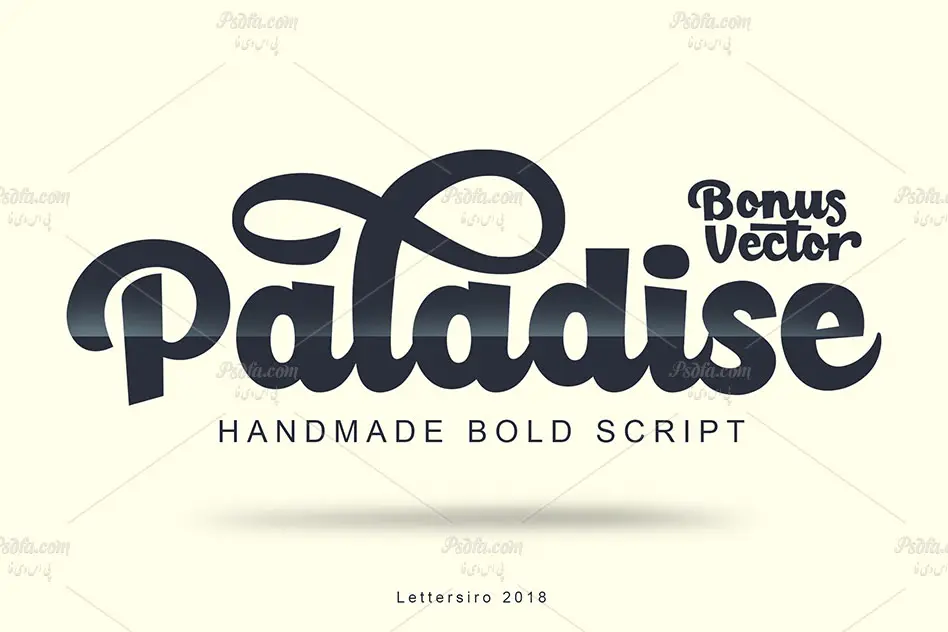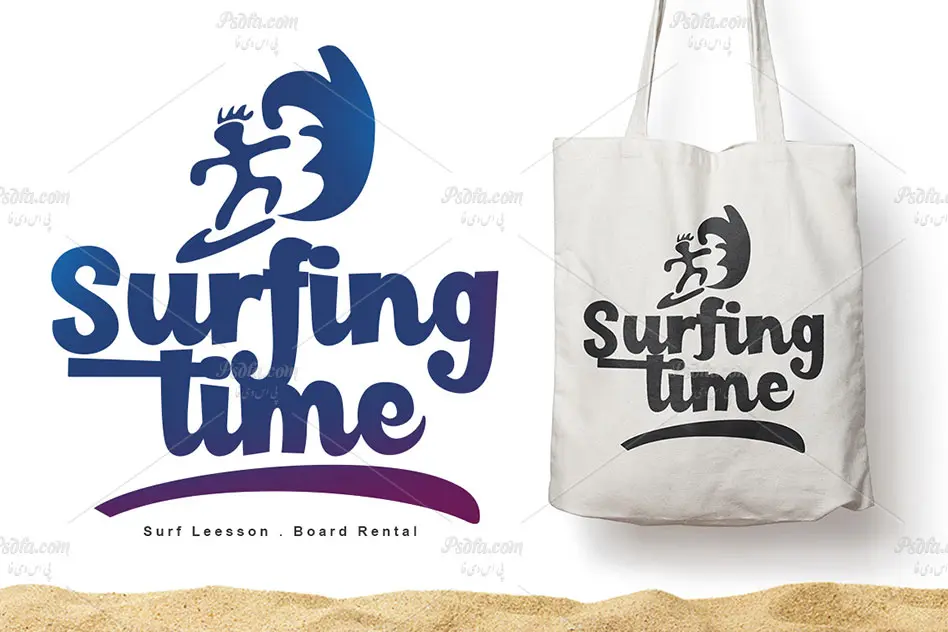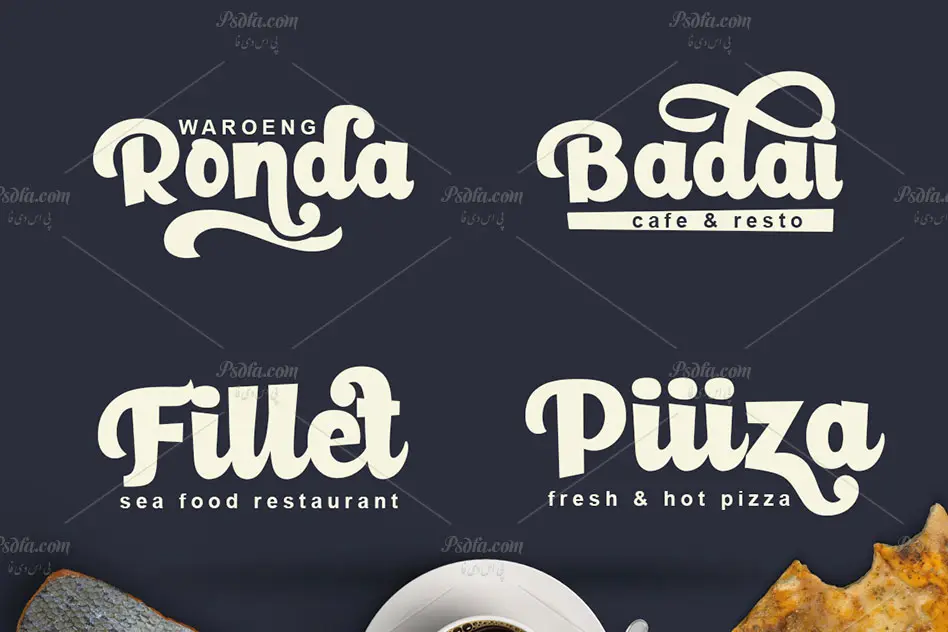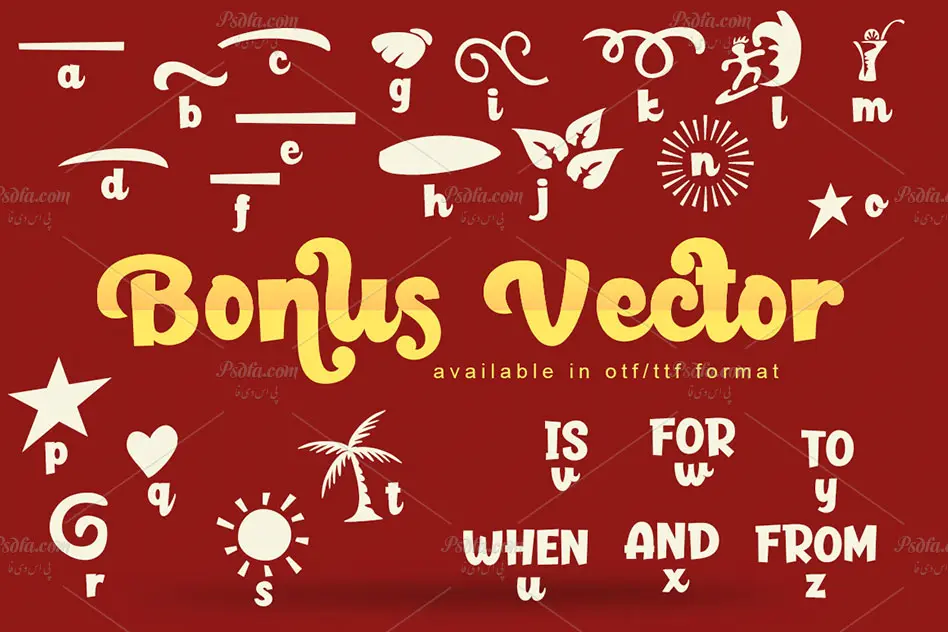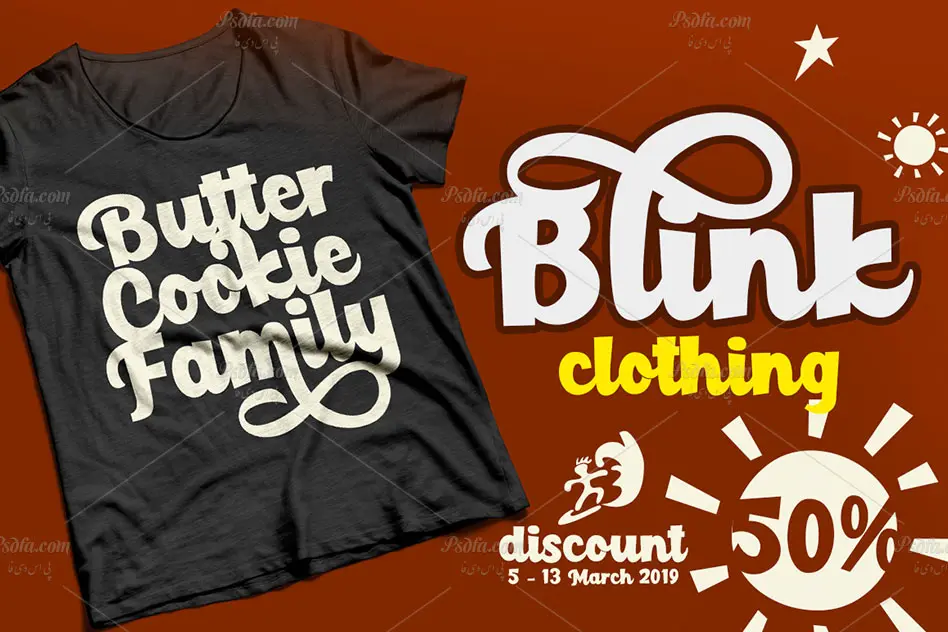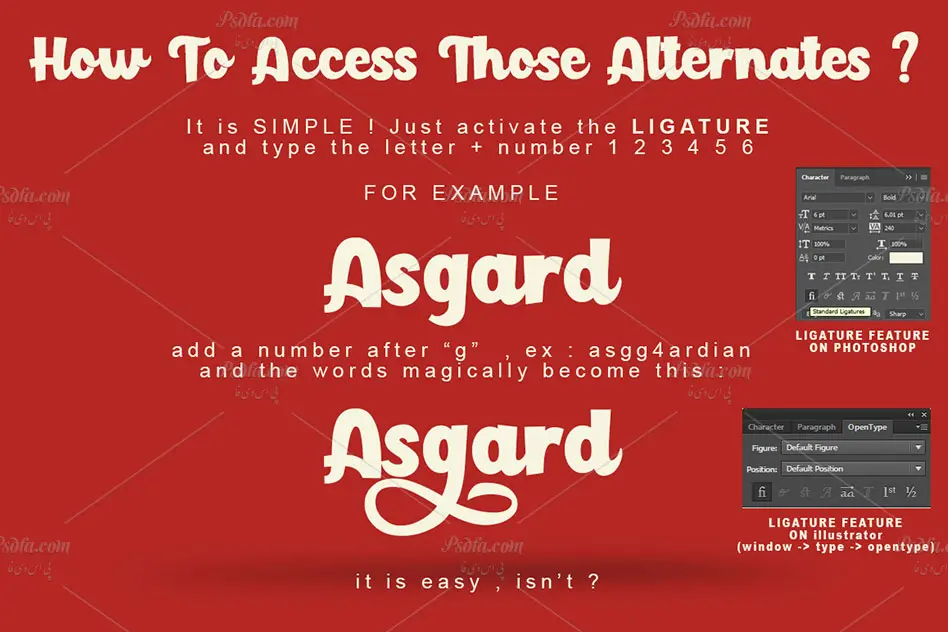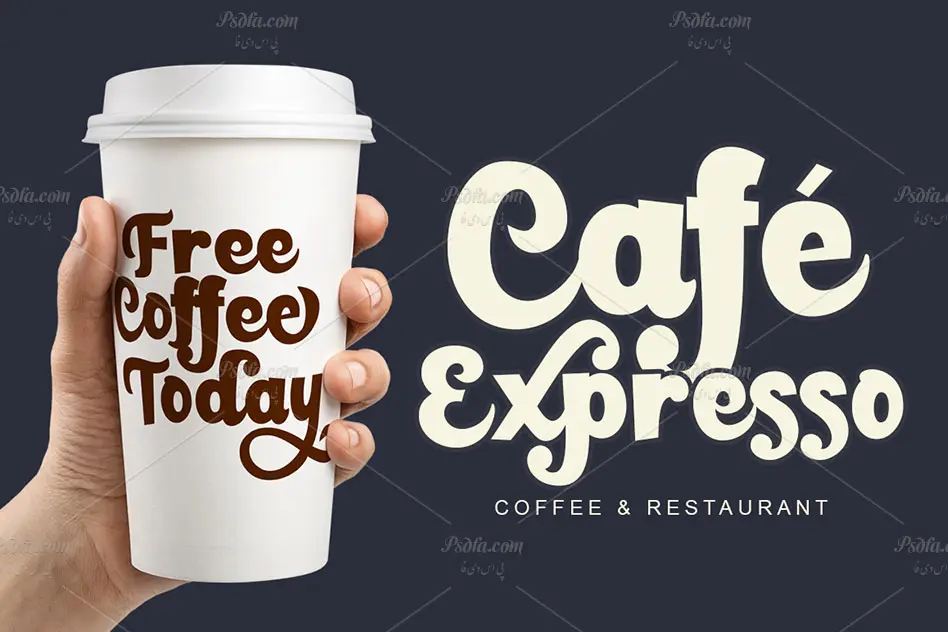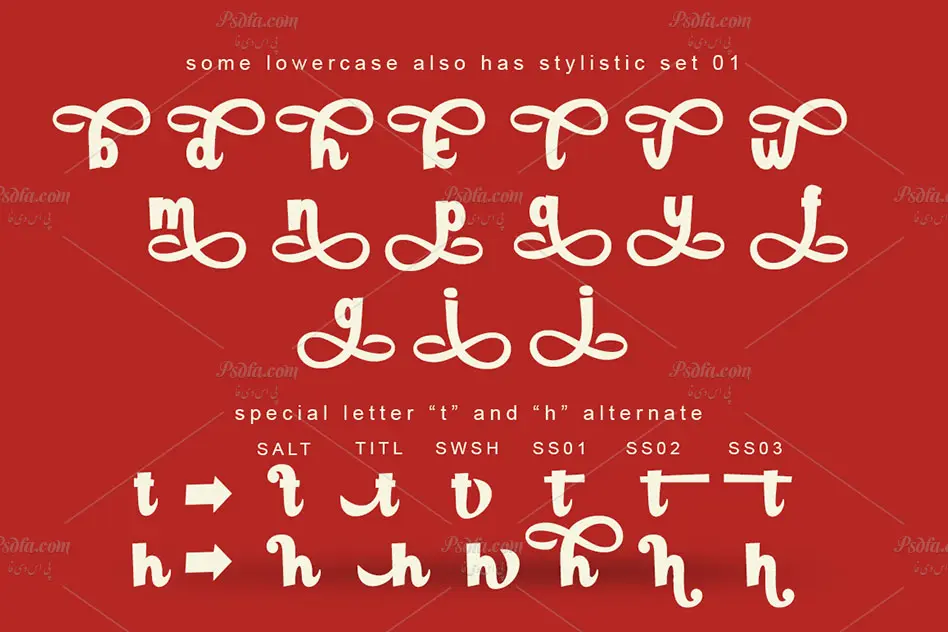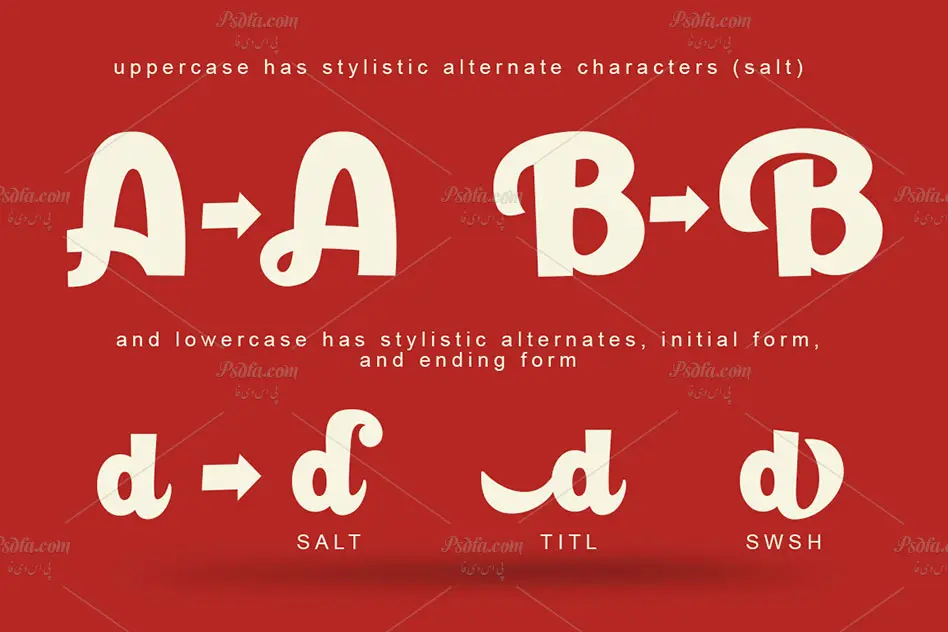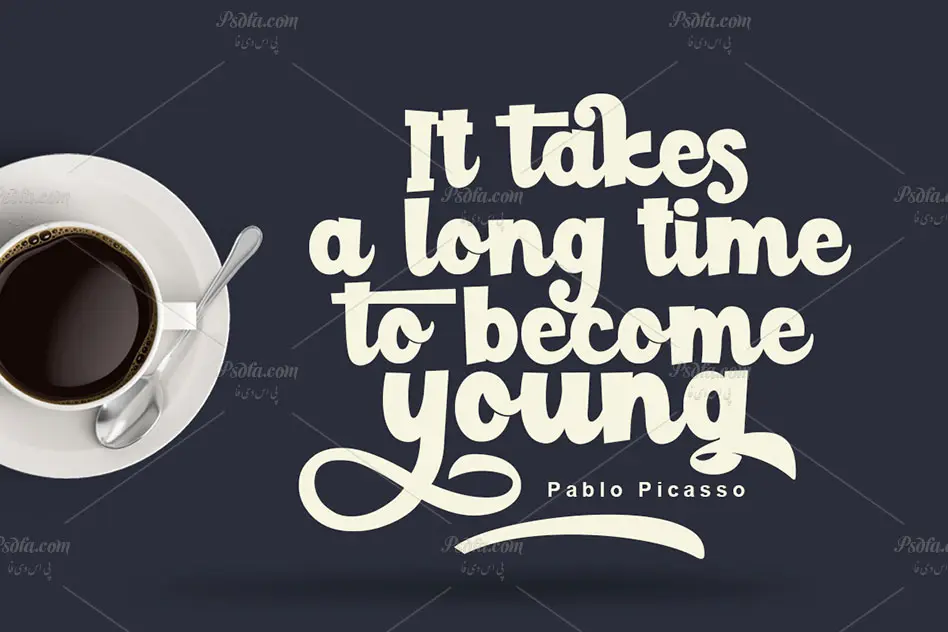
در این مطلب شاهد یکی دیگر از سری فونت های انگلیسی و دستنویس تحت عنوان Paladise می باشید. این فونت فوق العاده زیبا در قالب 4 فایل ttf و otf در سایت قرار گرفته اند که پس از نصب یکی از این دو فرمت در پوشه فونت های سیستم قادر به استفاده از آن ها در تمام نرم افزارهای گرافیکی و ویرایشگر متن از جمله نرم افزار فتوشاپ ، مجموعه نرم افزار آفیس و … می باشید. با نصب فونت Paladise Bonus که یک نوع فونت سمبل است می توانید از اشکال تزئینی این فونت نیز در طرح های خود بهره مند شوید. از فونت Paladise می توان در طراحی انواع پوستر ، تراکت ، کارت ویزیت ، طراحی بر روی پارچه و لباس ، طراحی بر روی بسته بندی محصولات ، طراحی بر روی ظروف سلولزی و … استفاده نمود.
- به همراه فونت سمبل اشکال تزئینی